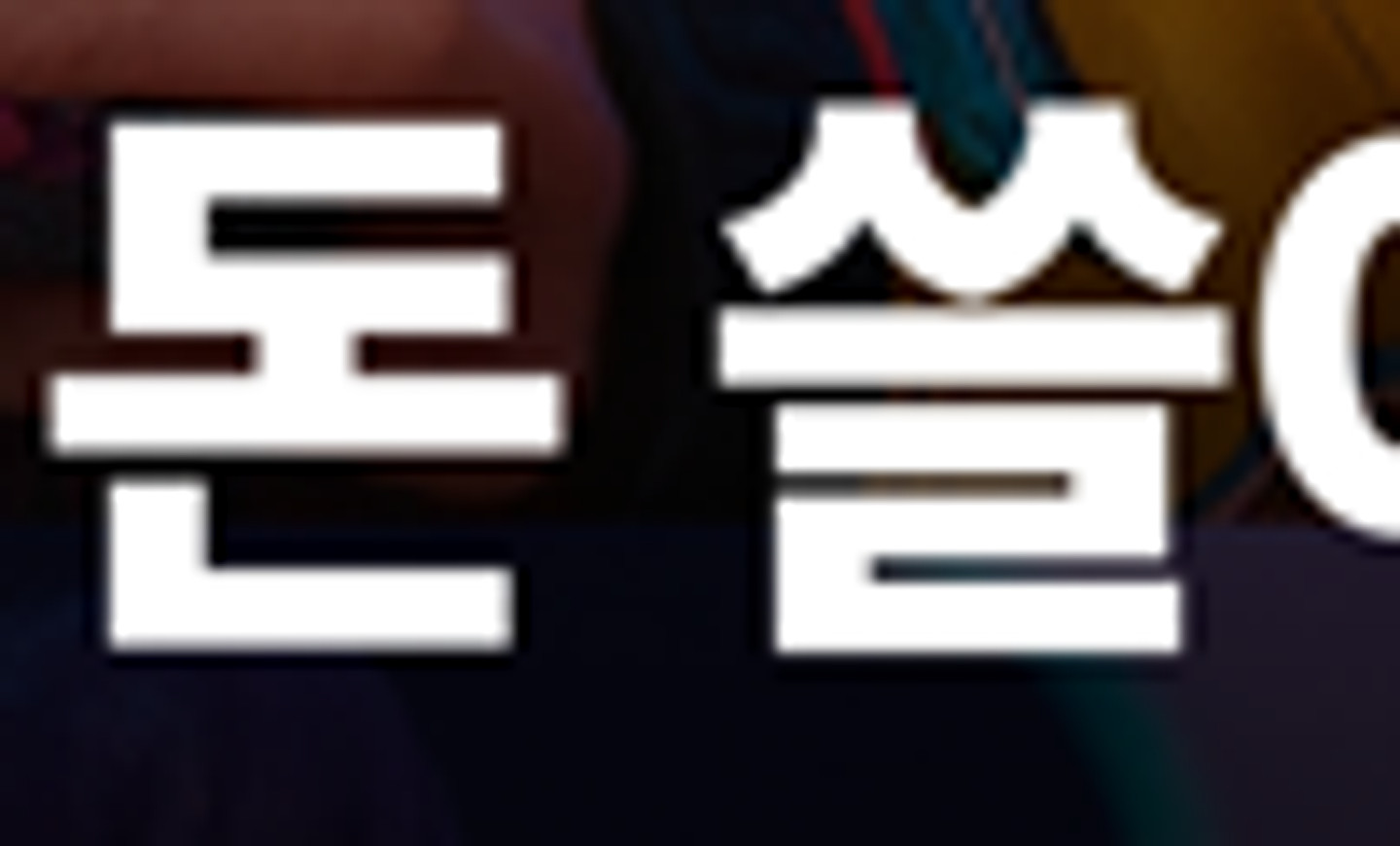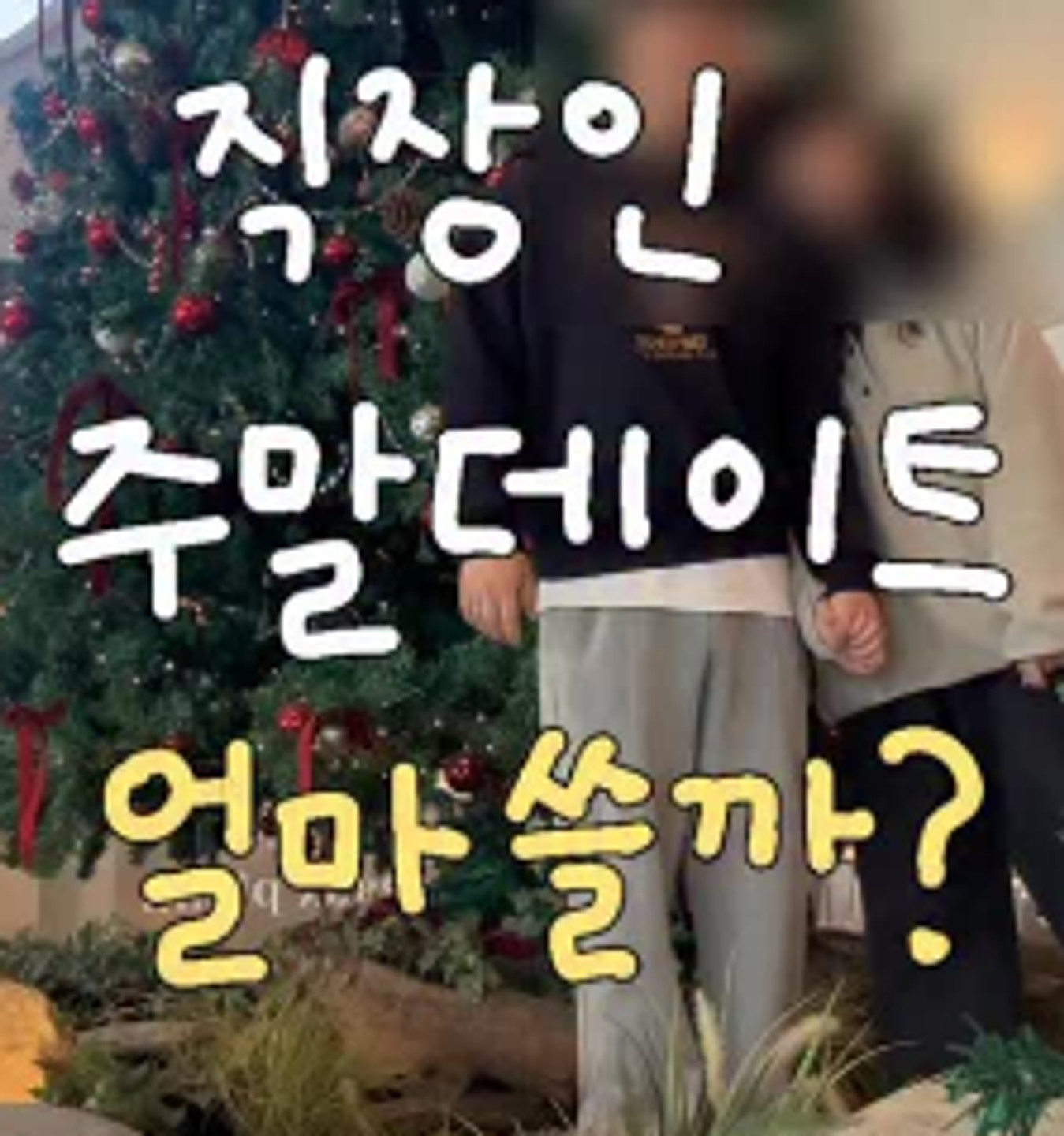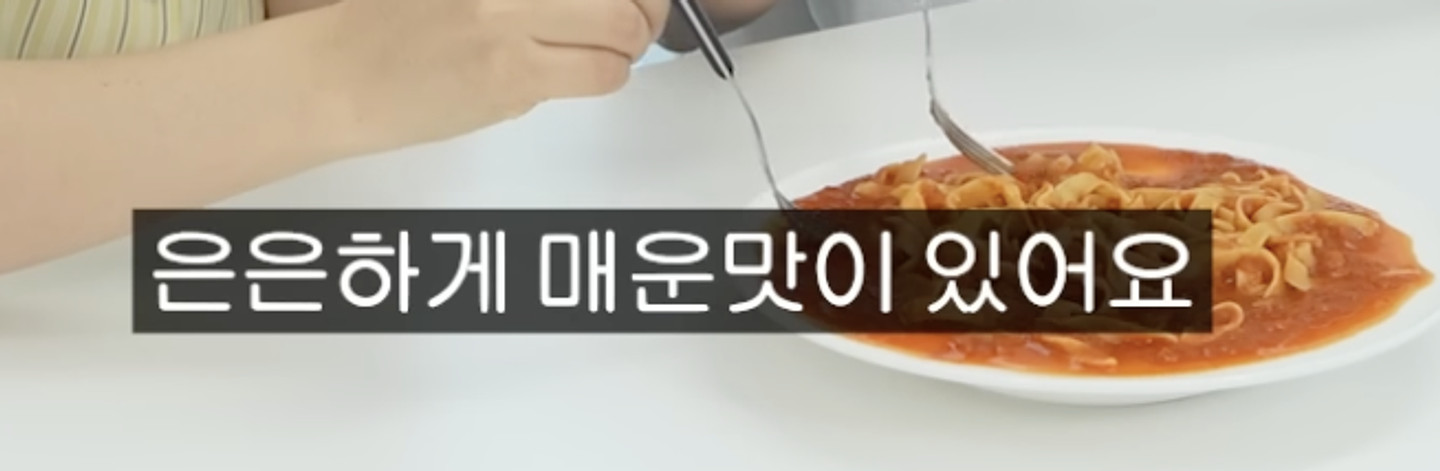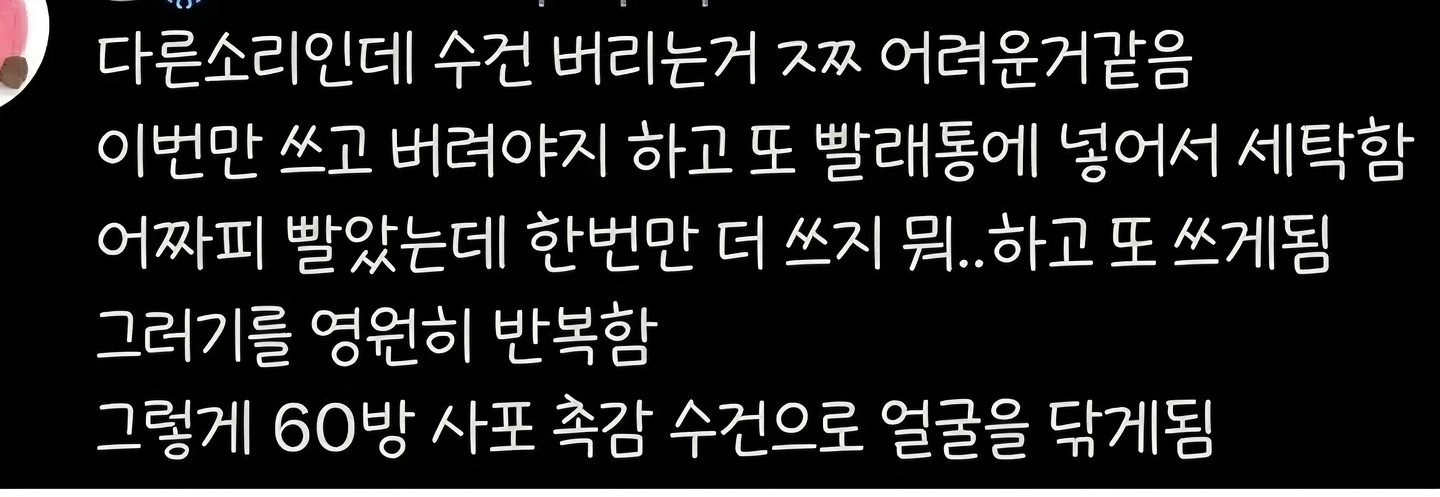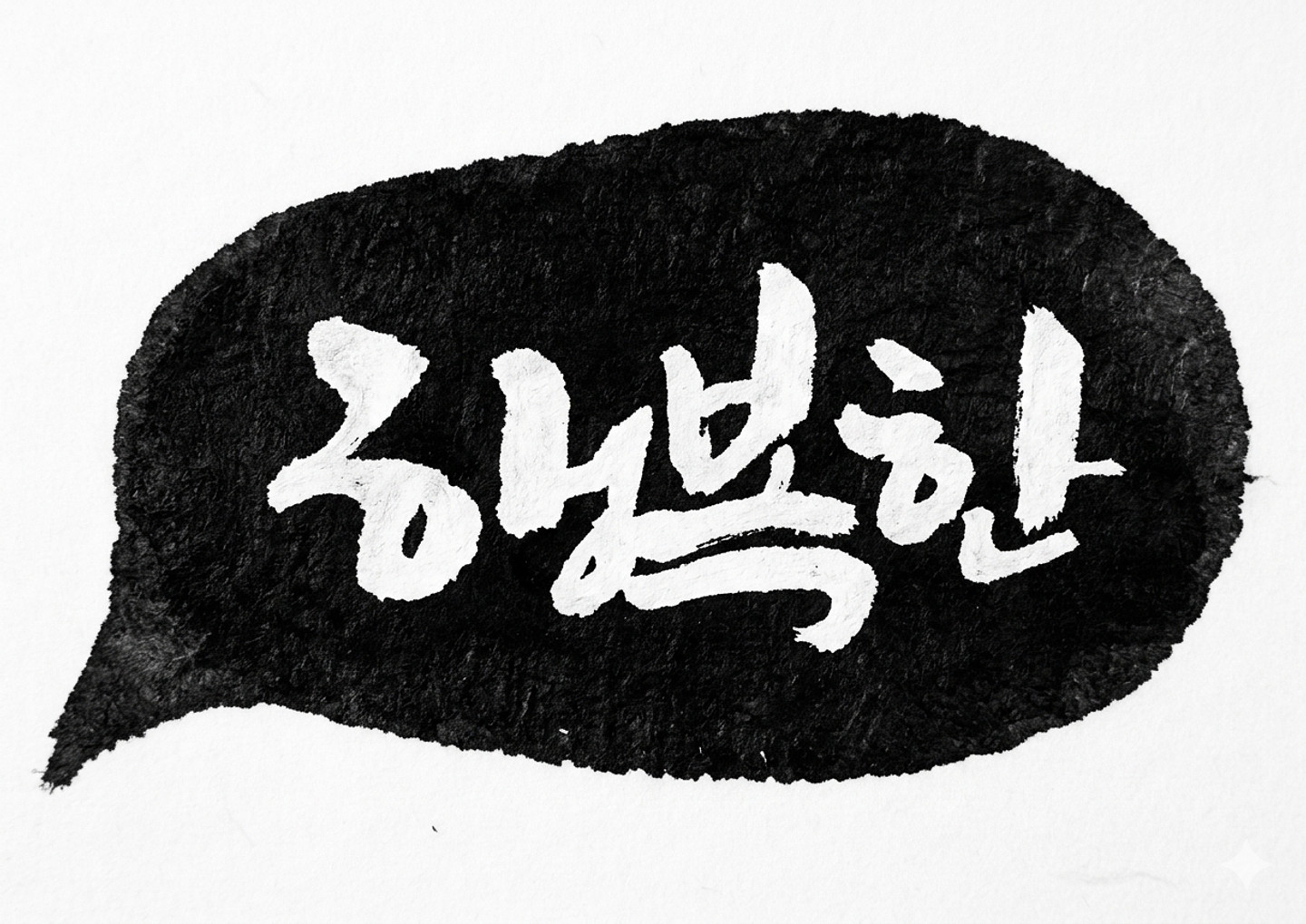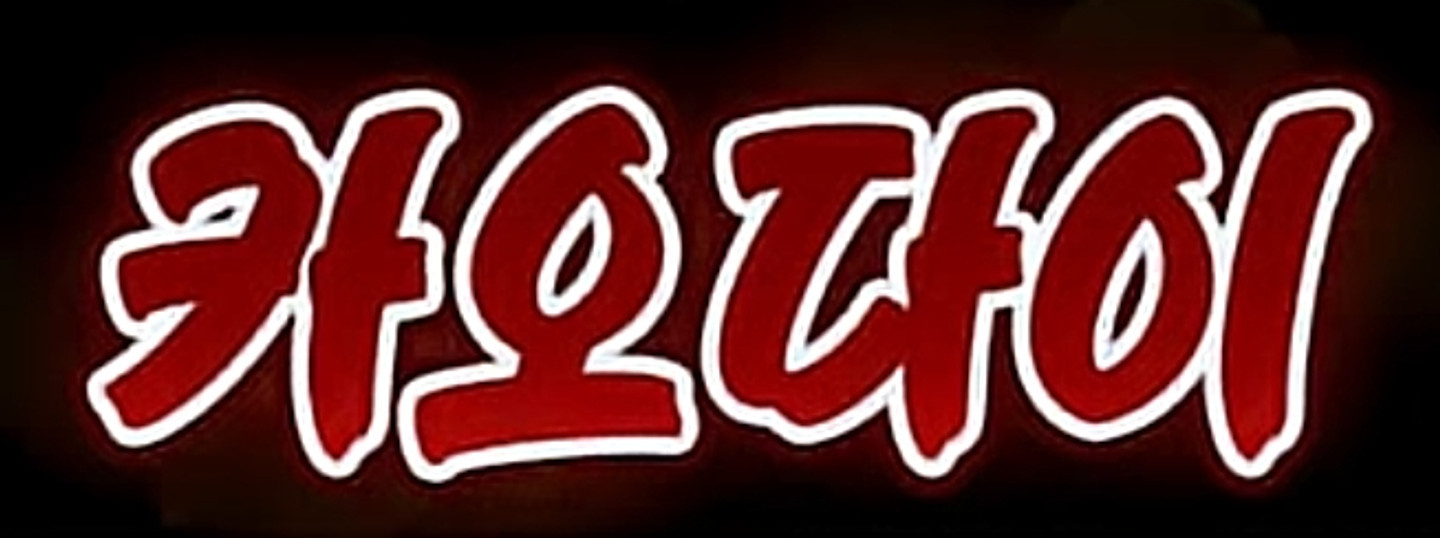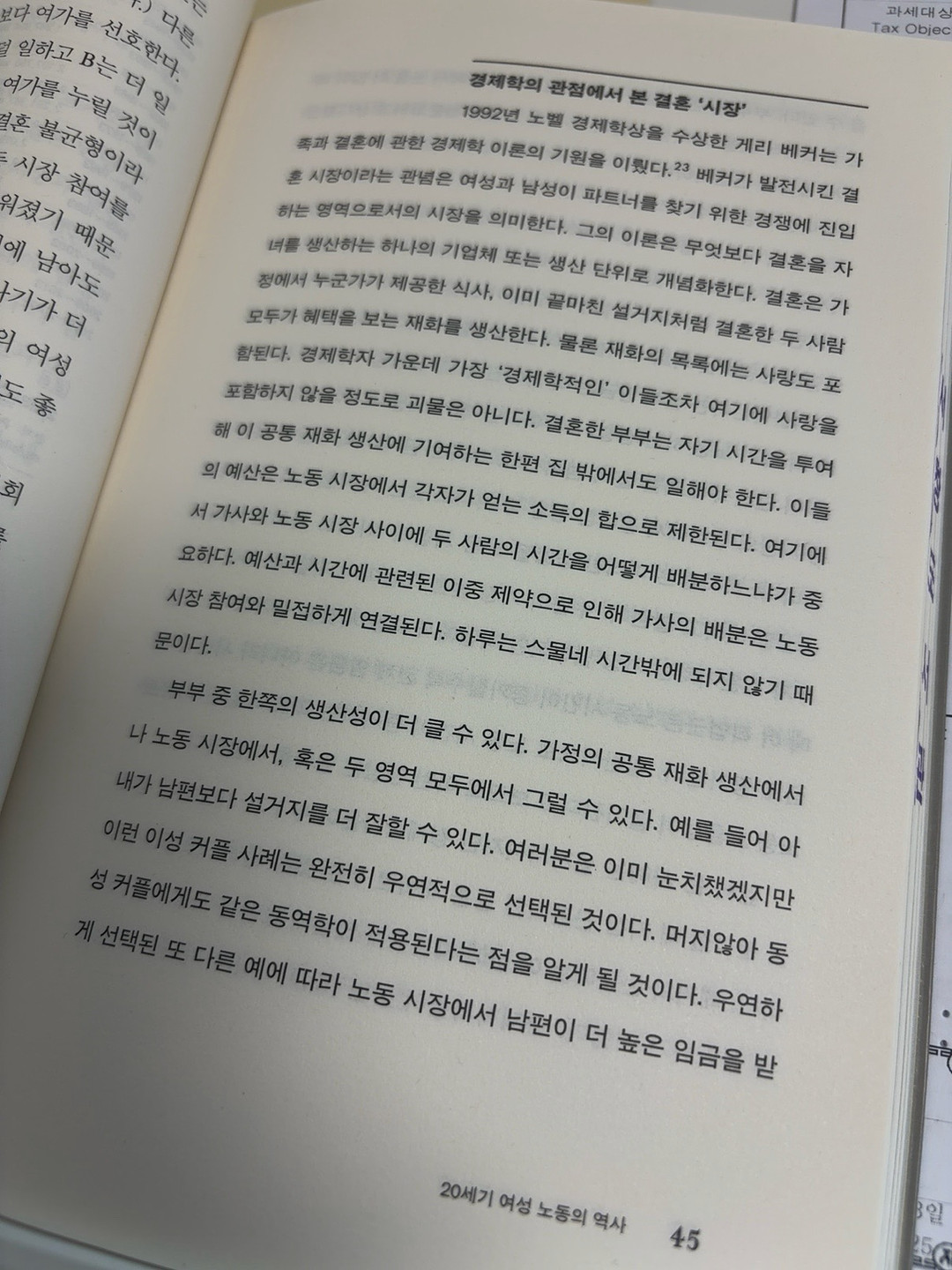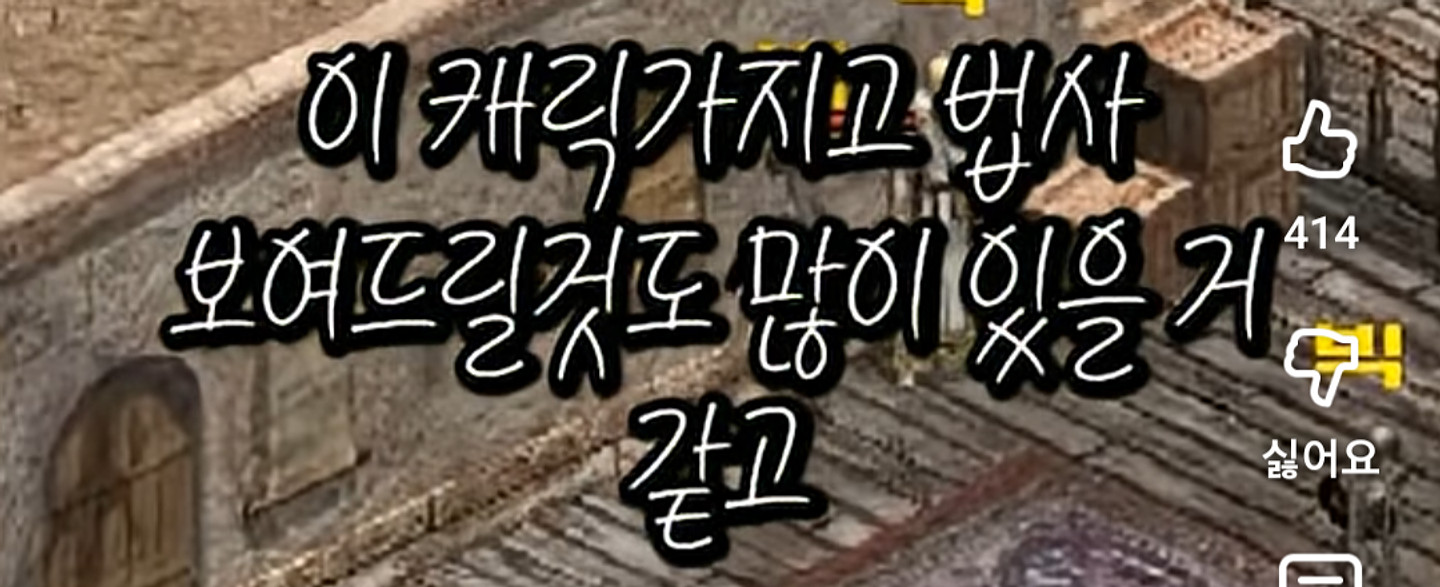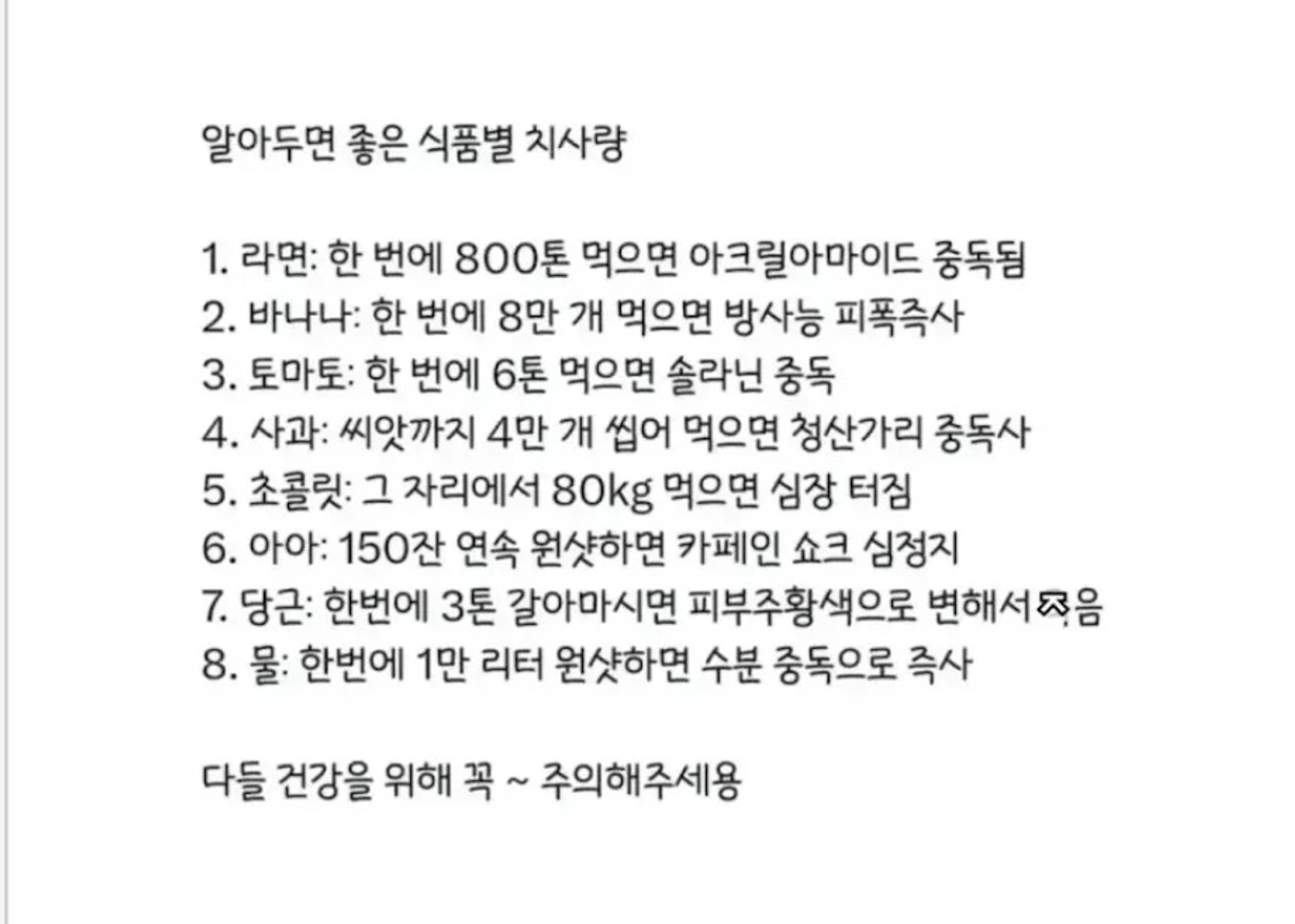
알려주세요 ㅠㅠ 아네모네에어?보다 ㅅ 꺾이는 부분이 더 커요
여기 썸네일용으로 사용한 흰색 연두색 폰트 뭔지 궁금해요
여기 썸네일용으로 사용한 흰색 노란색 폰트 뭔지 궁금해요
무슨 폰트일까요? (스포티비)
카톡음악엽서에 올라온 글씨인데요 아는분 계시면 알려주셨으면 합니다.
해당글씨체는 무슨 폰트일까요??
이건 무슨폰트일까요?
이 폰트 뭔지 궁금합니다 ㅜㅡㅜ!!
바로 채택!! 이 영문폰트 Awazero에서 만든 타이포그래피인데 폰트 다운 파일로는 없어서 비슷한걸로 궁금합니다! 절단부분이 수평수직인 폰트였으면 좋겠습니다! 서체의 연결부에 액체 같은 곡선은 없어도 됩니다!
영어 정말 알고싶어요
둘 다 궁금해요!
폰트 뭔가요ㅠㅠ
이거 글씨체뭘까요
만화보다가 나온 건데 무슨 폰트일까요
한우돈 폰트 무슨폰트일까요?